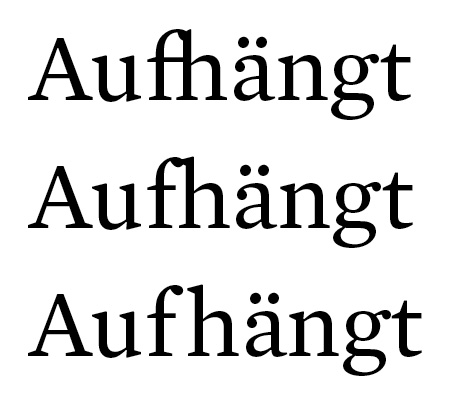
ich bin grad unschlüssig wie ich hier verfahre. die schrift
verfügt über eine fh-ligatur und diese kommt natürlich
im deutschen recht häufig ausserhalb des wortstamms vor.
normalerweise würde hier keine ligatur hingehören -
aber ohne ligatur (mitte) sieht es auch nicht sonderlich gut
aus und mehr space zwischen f und h (unten) geht garnicht!
was denkt ihr?
es handelt sich übrigens um reinen Lesetext in 9,5 Punkt auf
ca. 140 Seiten ...
die variante mit space reisst mir zu grpße lücken -
dann lieber die dezente kollision die man bei 9,5 punkt
eh nur bedingt wahrnimmt!
8)
Alles ist besser als Ligatur über Wortfuge. Besonders bei aufliegen, wo man automatisch hängenbleibt und au-fliegen liest. Das ist so brutal wie bei dem Schluß-s in Gasthof. Was Gas ist, weiß man ja – aber was ist ein Thof?
Aus Schriftgestalter-Sicht: Eine verkürzte f-Variante kontextabhängig verwenden.
- kollidiert/ligiert nicht
- reißt kein Loch
Muss allerdings in die Schrift eingebaut sein.
Ich verstehe Eure Diskussion überhaupt nicht.
Dort darf doch überhaupt keine Ligatur stehen:
Auch im Typo Wiki heißt es u.a.:
In der Regel werden Ligaturen nur gesetzt, wenn die zu verbindenden Buchstaben im gleichen Morphem liegen, also beispielsweise im Wortstamm. Ligaturen werden in der Regel nicht gesetzt, wenn sie eine grammatikalische Fuge (z. B. eine Wortfuge) trennt. „Kaufläche“ (Kau-fläche) wird daher mit fl-Ligatur geschrieben, hingegen wird bei „Kaufleute“ keine Ligatur verwendet, weil die Buchstaben f und l hier in verschiedenen Wortteilen (Kauf-leute) stehen. Eine Ausnahme bilden Nachsilben, die mit i beginnen (-ig, -in, -ich, -isch). Hier werden auch über die grammatikalische Fuge hinweg Ligaturen gesetzt. So wird beispielsweise „häufig“ trotz der Fuge (häuf-ig) mit fi-Ligatur geschrieben. Die Anwendung von Ligaturen ist jedoch nicht verbindlich geregelt, generell folgt man dem Grundsatz: Wenn die einzelnen Buchstaben getrennt gesprochen werden, wird keine Ligatur verwendet.